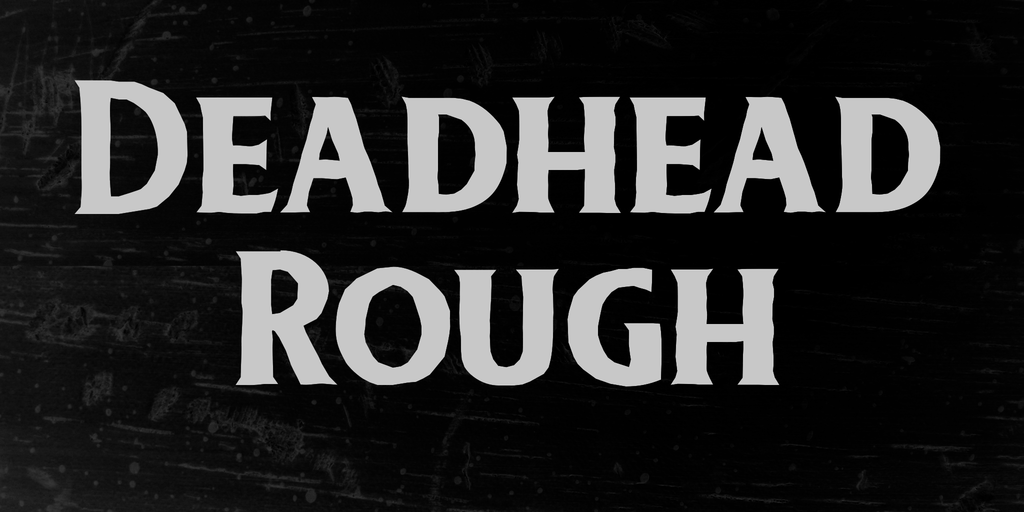
Deadhead Rough Font
A fonte ‘Deadhead Rough Font’ é uma elegante tipografia serifada que combina elementos levemente artesanais com um charme sofisticado. Desenvolvida pelo designer Hamilton, essa fonte é ideal para criações que exigem um ar de confiabilidade e profissionalismo. Se você deseja incorporá-la em projetos comerciais, a receita está simplesmente no clique do botão ‘DONATE’. Para usuários individuais ou não necessitando da permissão comercial, ela se torna uma fonte versátil para projetos pessoais e projetos educacionais. Esta fonte é perfeita para criações que buscam um equilíbrio entre seriedade e criatividade, fazendo-a uma opção valiosa na sua biblioteca de recursos gráficos.